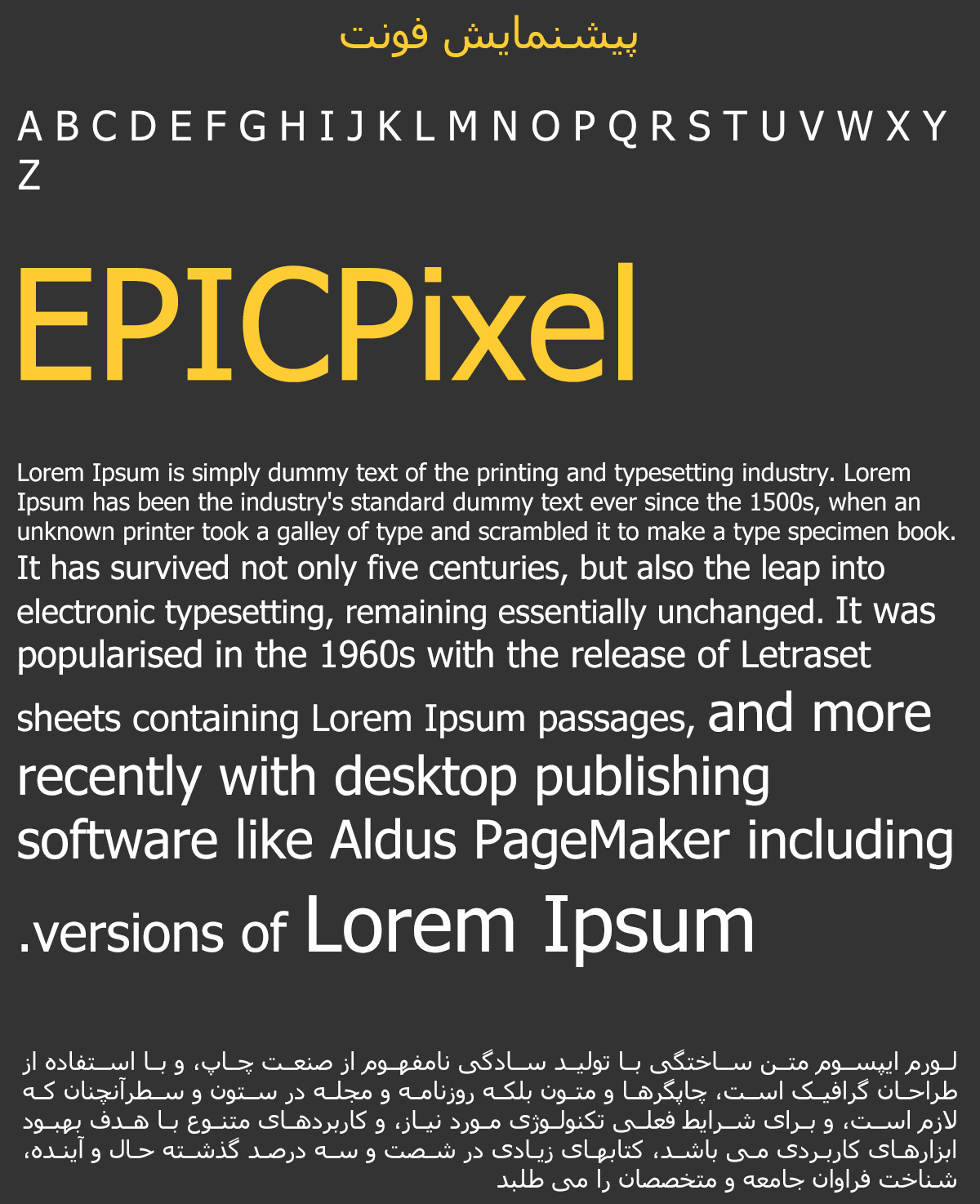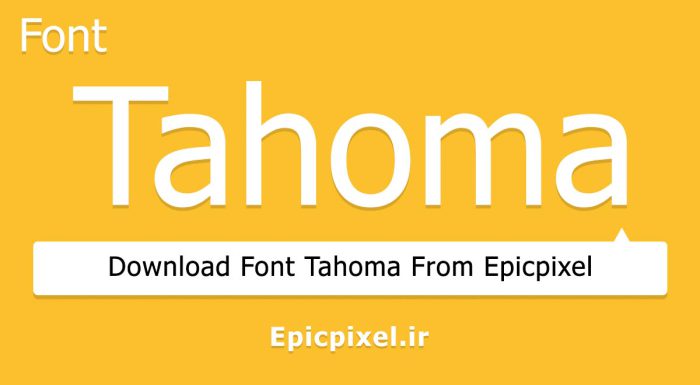
2 فونت Tahoma انگلیسی
فونت Tahoma یک تایپ فیس سان سریف انسانی (Humanist sans-serif) است که توسط Matthew Carter برای مایکروسافت طراحی شد. این فونت در سال ۱۹۹۵ همراه با سیستم عامل Windows 95 منتشر گردید. Tahoma به دلیل خوانایی بالای خود در صفحات نمایش، شکل باریک، فاصله گذاری تنگ حروف و قابلیت تمایز آسان بین حروف مشابه (مانند “I” بزرگ و “l” کوچک) شناخته شده است. این فونت، با دو وزن Regular و Bold عرضه می شود و هیچ سبک ایتالیک رسمی ندارد. Tahoma به عنوان فونت پیش فرض در ویندوز ۲۰۰۰، XP و Server 2003 و همچنین در اسکایپ و بسته بندی Dreamcast سگا استفاده شده است. این فونت برای استفاده شخصی رایگان است.
فونت Tahoma انگلیسی: قلمی خوانا و فشرده برای نمایشگرها
فونت Tahoma یکی از فونت های مهم و پرکاربرد در اکوسیستم مایکروسافت است که به طور خاص برای بهینه سازی خوانایی بر روی صفحات نمایش طراحی شده است. این فونت توسط Matthew Carter، طراح مشهور فونت، برای شرکت مایکروسافت طراحی شد و در سال ۱۹۹۵ به عنوان یک فونت سیستمی با ویندوز ۹۵ منتشر گردید.
طراحی و ویژگی ها:
- سان سریف انسانی و باریک: Tahoma یک تایپ فیس سان سریف با ویژگی های انسانی است. این فونت بر اساس فونت Verdana (یکی دیگر از فونت های Carter) طراحی شده، اما دارای بدنه ای باریک تر، فضاهای داخلی کوچک تر (counters) و فاصله گذاری حروف بسیار تنگ تر است.
- خوانایی بالای روی صفحه: همانند Verdana، Tahoma نیز به طور خاص برای خوانایی آسان بر روی صفحات نمایش (حتی در اندازه های کوچک) طراحی شده است، اگرچه در چاپ نیز به خوبی عمل می کند. این ویژگی به لطف “اشارات فونت” (font-hinting) فنی توسط Tom Rickner به دست آمده است.
- تمایز حروف: یکی از ویژگی های برجسته Tahoma، قابلیت تمایز آسان بین حروف مشابه مانند “I” بزرگ (حرف I) و “l” کوچک (حرف L) است که در بسیاری از فونت های سان سریف دیگر ممکن است گیج کننده باشد. این امر به ویژه در متون فنی و اسنادی که نیاز به دقت بالا دارند، اهمیت پیدا می کند.
- حس باز و واضح: Tahoma حس شفاف و بازی دارد و به دلیل طراحی متراکم خود، برای شرایطی که نیاز به جای دادن کلمات زیاد در فضای کم است (مانند ستون های باریک خبرنامه ها، سرفصل ها یا زیرنویس ها در صفحه گوشی) بسیار مفید است.
وزن ها و سبک ها: فونت Tahoma دارای دو وزن مشخص است:
- Tahoma Bold اما فاقد سبک های ایتالیک (مورب) رسمی است. از سال ۲۰۱۰، Ascender Corporation نسخه های ایتالیک و حروف کوچک (small caps) Tahoma را ارائه کرده است.
تاریخچه و توزیع:
- Tahoma همراه با Office 97، Office 2000 و Office XP ارائه شد و با Word Viewer 97 نیز به صورت رایگان توزیع می گردید.
- این فونت به عنوان فونت پیش فرض صفحه نمایش در ویندوز ۲۰۰۰، Windows XP و Windows Server 2003 (جایگزین MS Sans Serif) و همچنین در ویندوز ویستا، ویندوز ۷ و ویندوز سرور ۲۰۰۸ R2 در زمان استفاده از تم کلاسیک ویندوز، استفاده می شد.
- Tahoma همچنین در اسکایپ و برای بسته بندی و مواد تبلیغاتی Dreamcast سگا نیز به کار رفته است.
- در سال ۲۰۰۷، اپل اعلام کرد که Tahoma در نسخه بعدی macOS X v10.5 (“Leopard”) گنجانده خواهد شد.
کاربردهای فونت Tahoma در طراحی و اسناد
فونت Tahoma به دلیل طراحی باریک، خوانایی بالا و حضور گسترده در سیستم عامل ها، در طیف وسیعی از کاربردها در اسناد، طراحی وب، و رابط های کاربری مورد استفاده قرار می گیرد.
کاربردهای اصلی:
- فضاهای محدود: این فونت برای موقعیت هایی که نیاز به جای دادن حجم زیادی از متن در فضای محدود است (مانند ستون های باریک خبرنامه ها، عناوین و زیرنویس ها در صفحه گوشی)، بسیار مفید است.
- عناوین و سرفصل ها: Tahoma می تواند به عنوان فونت اصلی برای سرفصل های گزارش ها یا ارائه ها که از Verdana برای متن اصلی استفاده می کنند، به کار رود.
- برچسب ها، زیرنویس ها و علائم: به دلیل وضوح و خوانایی، برای برچسب گذاری، زیرنویس ها و علائم مناسب است.
- رابط کاربری (UI): به عنوان یک فونت سیستمی در ویندوز، در جعبه های گفتگو و منوها کاربرد گسترده ای داشته و دارد.
- متون دیجیتال: به دلیل بهینه سازی برای نمایشگرها، برای متون وبسایت ها و برنامه های دیجیتال که خوانایی در صفحه نمایش اهمیت دارد، مناسب است.
- محتوای فنی: به دلیل تمایز واضح بین حروف مشابه (I و l)، برای انتشارات فنی که دقت در خواندن کاراکترها حیاتی است، مفید است.